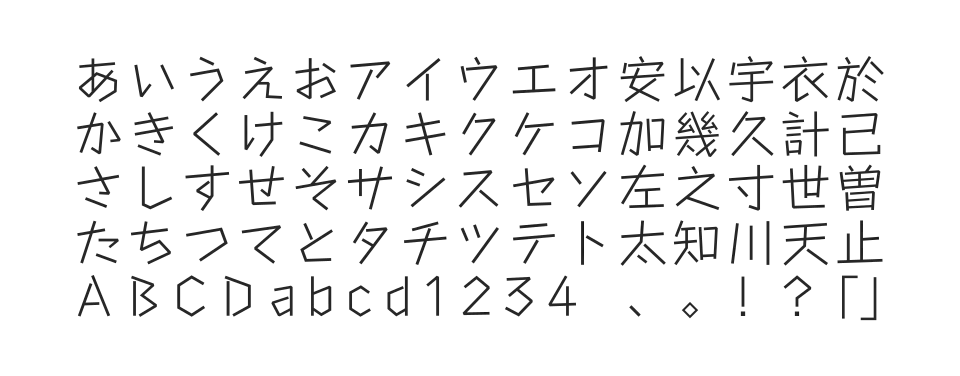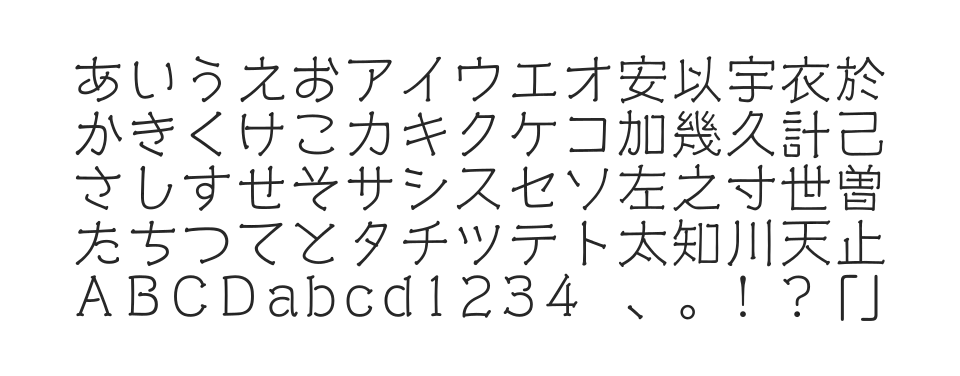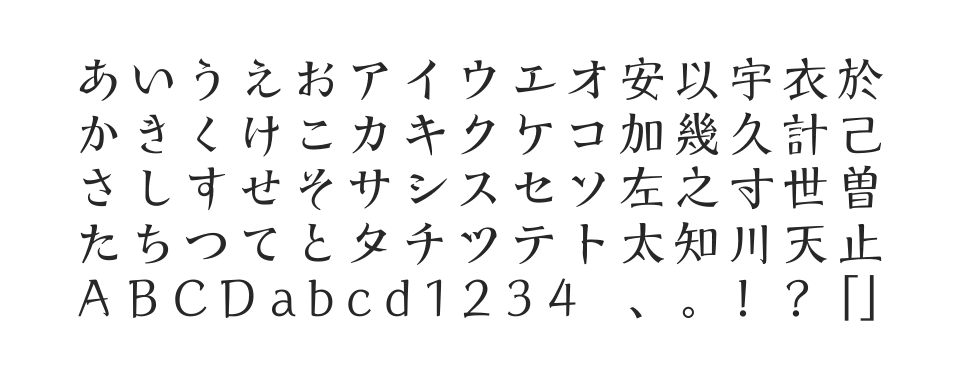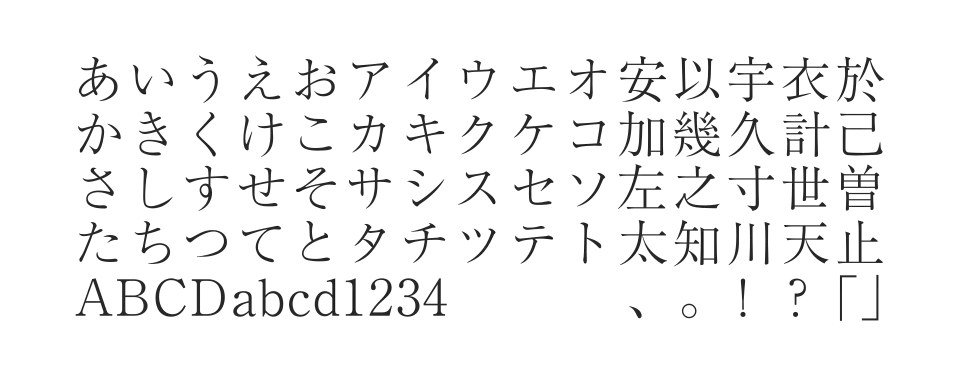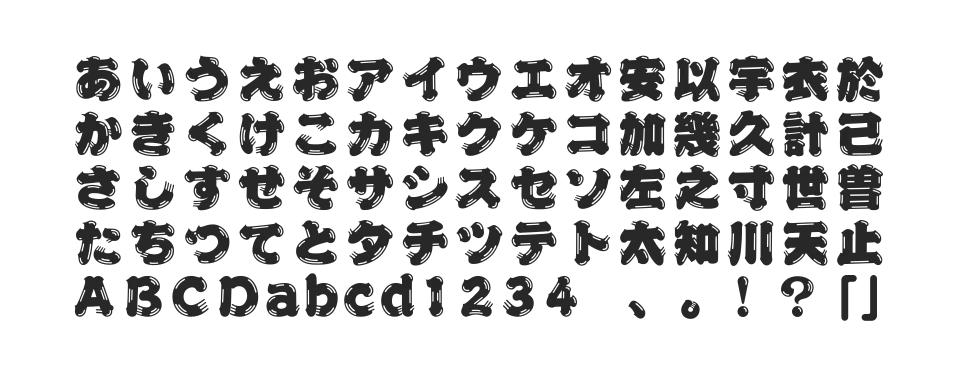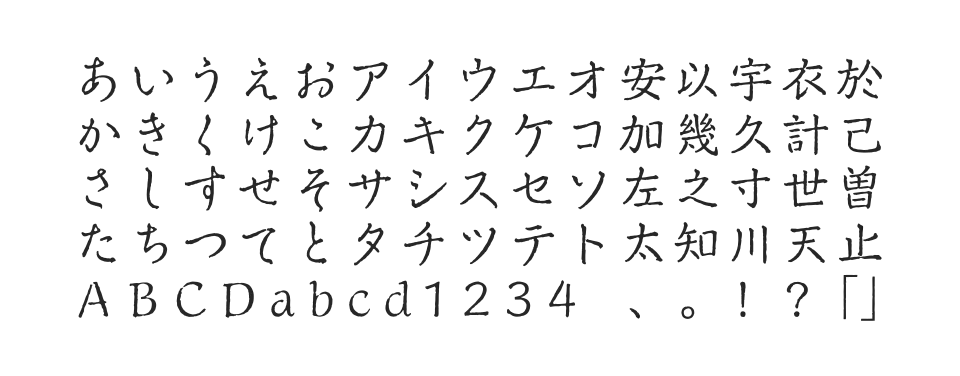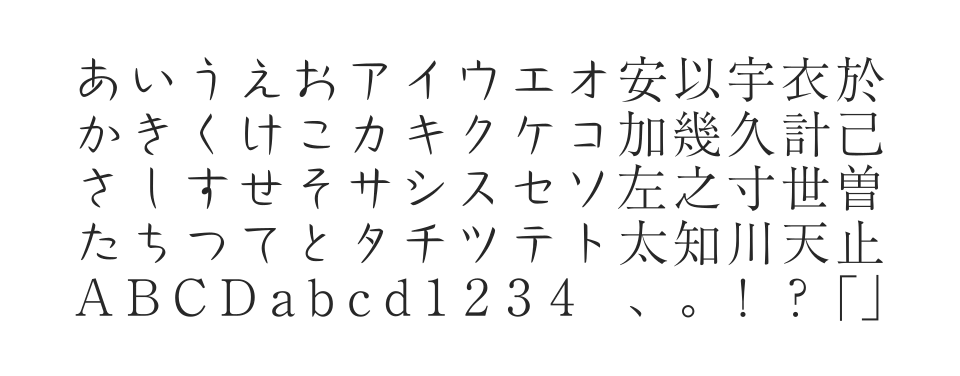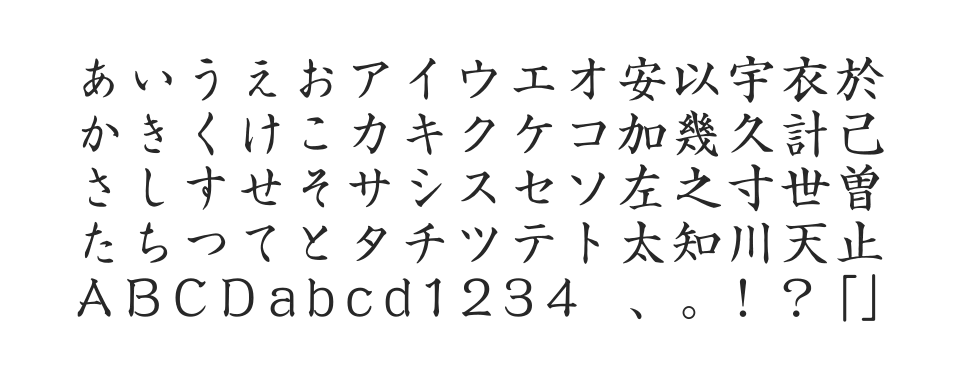
森川龍文堂明朝体をベースに開発したスタンダードな明朝体。金属活字の彫刻刀の冴えを活かしつつ、縦画・横画の先端にやわらかさを持たせた親しみやすい書体です。
正確な筆法と力強い書風で使いやすいオーソドックスな楷書体。筆の入り方や太さに安定感のある縦画、りりしくシャープな右上がりの横画が特徴の格調高い書体です。
森川龍文堂明朝体をベースとしたスタンダードな明朝体のPr6N版。23,058字の豊富な文字セットを収録し、流れるような表情の美しさに定評があります。
繊細でやわらかい筆の運びが印象的なかなデザイン書体。草書の運筆を取り入れた和のイメージが上品な印象を与え、様々な書体と組み合わせることができます。
手になじんだ万年筆でなにげなく書き綴ったような趣きと知性を感じさせる書体。味わいのあるにじみの表現で手書きのタッチや紙の質感を演出します。
極太の筆で勢いよく描いたような力強い筆書体。1977年のモリサワ写植文字盤用書体を復刻。墨のかすれと終筆部の髭が特徴で日本の祭のような生命力を表現します。
森川龍文堂明朝体をベースに開発したスタンダードな明朝体。金属活字の冴えを活かしながらやわらかさをもたせ、DTPの基本書体として幅広く使用されています。
特徴ある自由なエレメントをもったオリジナル書体。明朝体に近いコントラストがあり、親しみやすく強さとやわらかさを兼ね備えたスタイルです。
約30年にわたり映画字幕文字を書き続けている職人の文字をもとに作成。レトロな雰囲気で映画関係のデザインや温かみを演出したい本文に最適です。
モリサワが開発したA P-OTF書体シリーズの一つ。和文・欧文ペアカーニング機能を搭載し、より美しい文字詰めを実現する日本語フォントです。